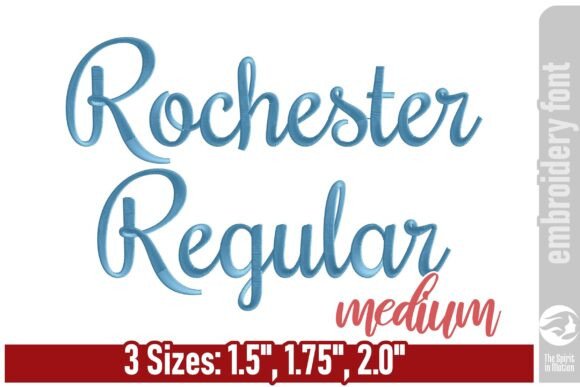
Rochester Embroidery Font - Medium
Trouver les bons éléments de conception peut être un défi, mais Rochester Embroidery Font - Medium propose une collection exceptionnelle qui rehausse instantanément votre travail.
Conçu avec précision, Rochester Embroidery Font - Medium offre des vecteurs nets, une typographie fluide et une licence commerciale pour une tranquillité d'esprit.
Que vous créiez des produits POD (impression à la demande), des invitations de mariage ou des visuels pour les réseaux sociaux, Rochester Embroidery Font - Medium est un choix idéal.